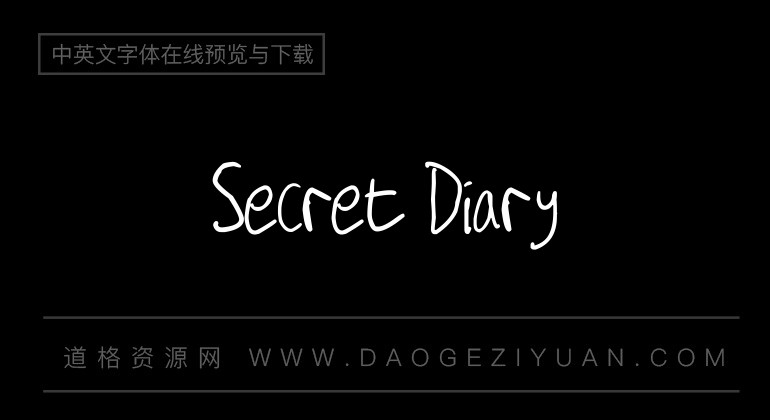
Secret Diary 是一种手写风格的字体,其字母和数字看起来像是用钢笔或铅笔书写而成。它的字体风格非常适合用于写日记、信件等私人用途的文本。它的字母和数字都有一些不规则的笔画和线条,看起来有些粗糙,但也正是因为这种手写风格,才更能够表达出文本的个性化和情感色彩。Secret Diary 字体可用于多种设计和文本排版中,比如卡片、海报、书籍等等。它也是一款比较受欢迎的免费字体之一,可以在许多字体网站上免费下载和使用。内容介绍
Secret Diary是一款非常不错的手写艺术字体,具有很好的视觉感,适合于文化类的宣传设计、商业类品牌的广告和产品包装设计以及个性化文字排版等较多场景。